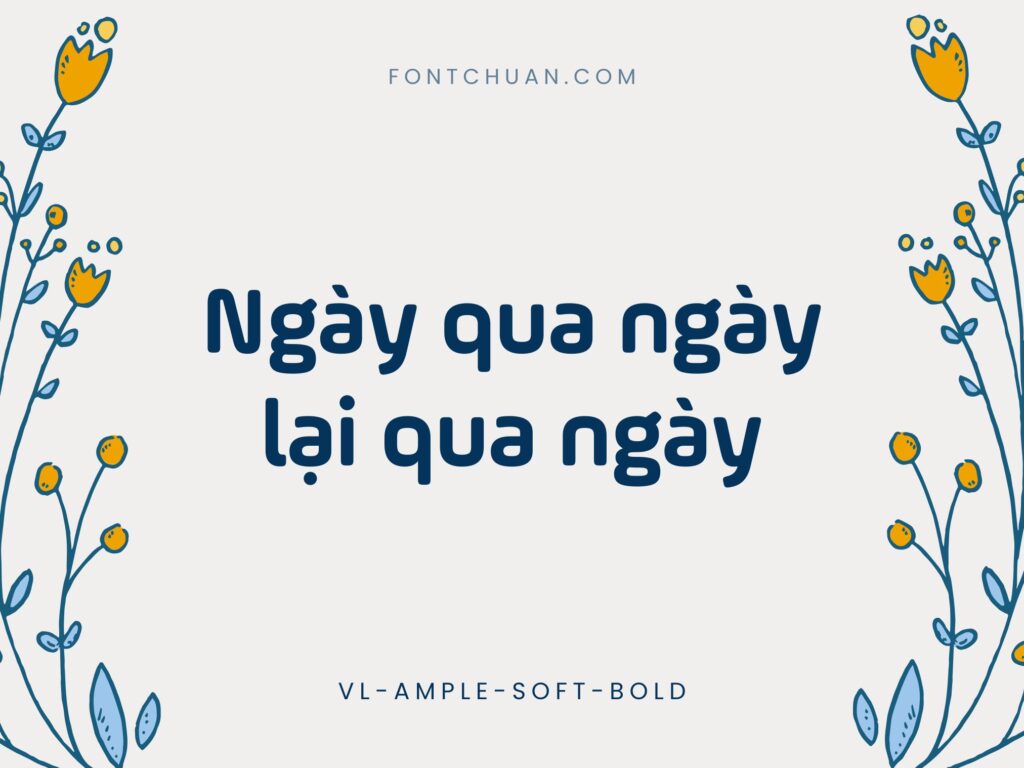
Font VL Ample Soft Trọn Bộ Việt Hóa
VL-Ample-Soft là một phông chữ sans-serif mang phong cách hiện đại và mềm mại, được thiết kế bởi Aakash Soneri. Phông chữ này có các đường nét mượt mà và góc cạnh được bo tròn, tạo nên sự thân thiện và dễ tiếp cận trong thiết kế. VL-Ample-Soft đã được Việt hóa bởi Việt Linh, hỗ trợ đầy đủ các ký tự tiếng Việt, giúp người dùng dễ dàng sử dụng trong các dự án sáng tạo. Phông chữ này được thành viên Font Chuẩn sưu tầm và đăng tải nhằm phục vụ nhu cầu thiết kế đa dạng.
Nhờ sự rõ ràng, thanh thoát và dễ đọc, VL-Ample-Soft còn là một Font chữ giáo dục lý tưởng, phù hợp để thiết kế sách giáo khoa, tài liệu học tập, bài giảng và các ấn phẩm đào tạo, mang đến trải nghiệm học tập dễ chịu và chuyên nghiệp cho người đọc.